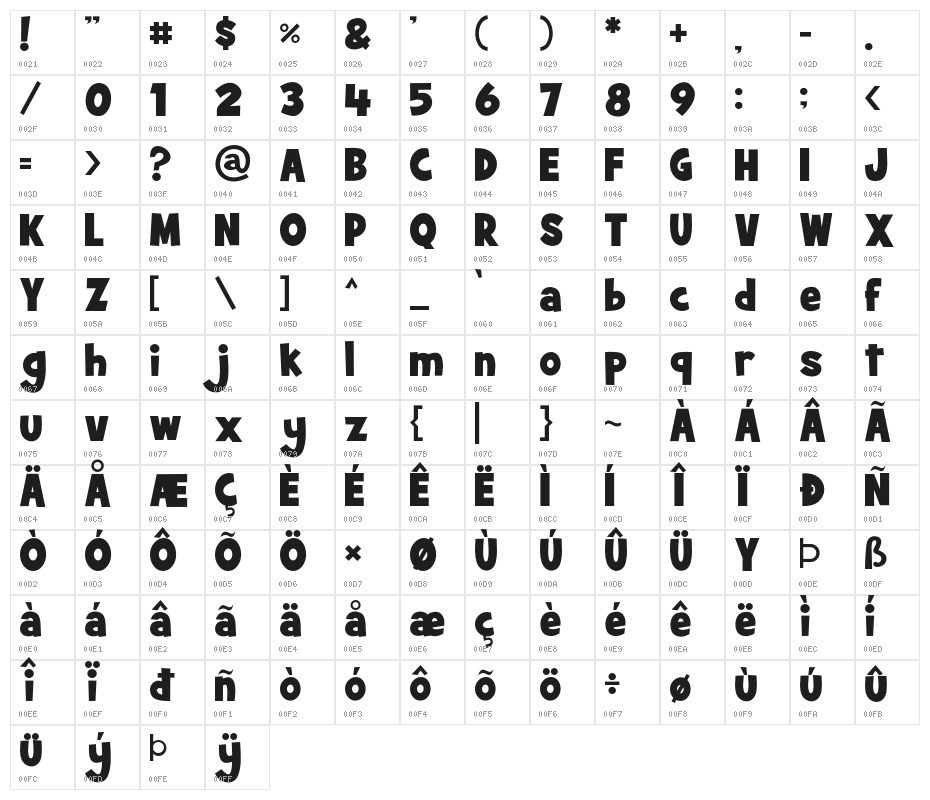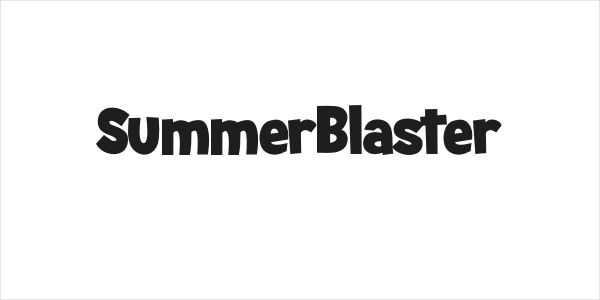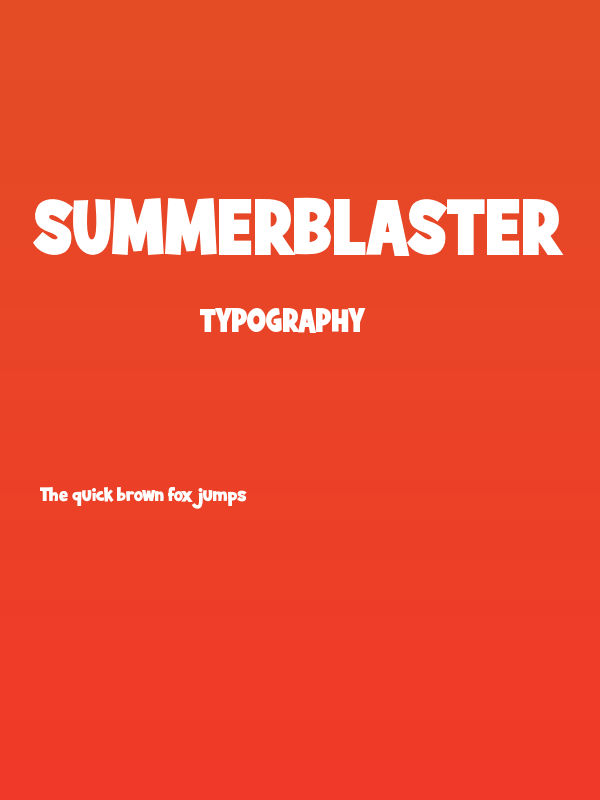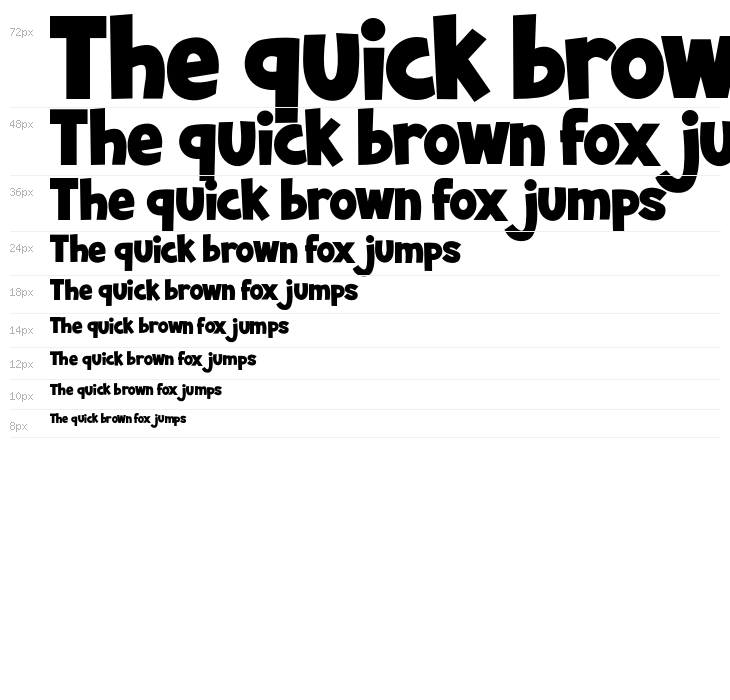
SummerBlaster Font
✎ Cartoon
| Gesamtstil | Playful |
| Vorgeschlagene Projekte | Ideal for children's book covers, playful branding, party invitations, and eye-catching posters. |